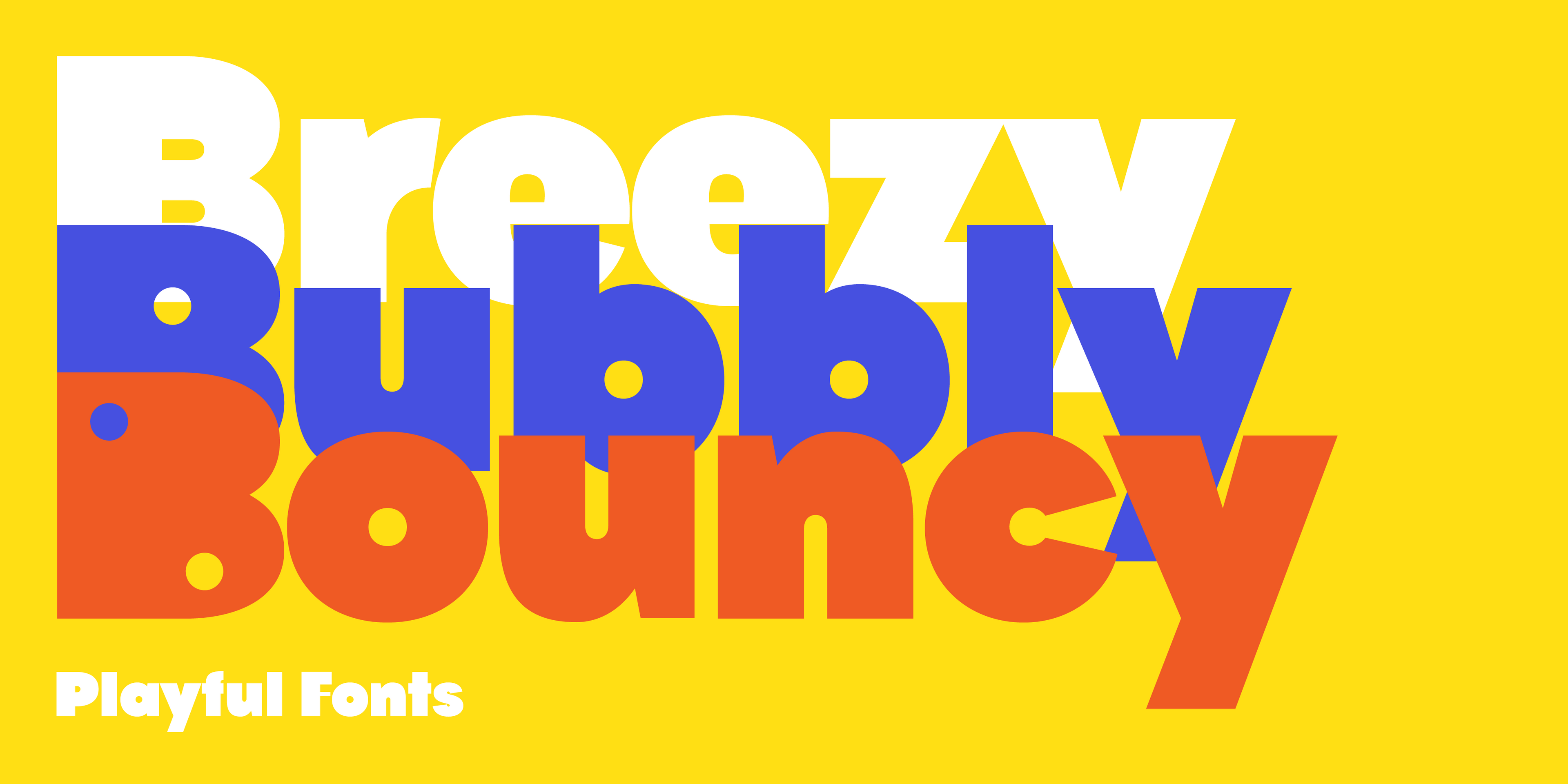
Ya sea que esté trabajando en la marca de un producto para niños o en un libro divertido de leer, las fuentes divertidas son una forma sencilla de comunicar rápidamente el concepto central de su proyecto.
En este artículo, verá algunas de las mejores fuentes gratuitas y comerciales disponibles y explicará por qué son ideales para esta colección de tipografías divertidas y qué tono específico logrará en sus diseños cuando las use.
Fuentes sans-serif divertidas para exhibiciones
Además de encontrar la fuente más divertida y genial para tu proyecto, no olvides probar una variedad de paletas de colores junto con tu texto en nuevas tipografías: los colores realmente pueden marcar una diferencia en cómo respaldan o equilibran el carácter de una tipografía.
Echa un vistazo a Bool arriba. Seleccioné el grosor más audaz de todos, Black. Esta fuente tiene muchos diseños de letras alternativos; en mi ejemplo, estás viendo diferentes letras B. Casi parecen juguetes; cámbialas si necesitas más caracteres de logotipo para tu texto. Más detalles sobre Bool .
Si buscas un estilo más alocado, prueba Pout , una tipografía de contraste inverso. Normalmente conocemos este estilo por las películas del Oeste, pero esta es sans-serif, lo que la hace moderna y divertida. Dado que el peso visual del diseño está en la parte superior e inferior, los trazos verticales de las letras se vuelven finos y las barras horizontales se vuelven llamativas. Los puntos i son redondos y llenos, lo que crea tensión y memorabilidad.
Un poco más estándar a primera vista, esta fuente sans-serif se llama Vole Display , que aquí se muestra en un peso de fuente ligero. Sin embargo, esta tipografía es muy divertida: los tallos inclinados (letras M, W), completamente redondeados y sin tallos que se extiendan por completo hasta la altura de la x para las letras a, m, n y r hacen que esta fuente sea accesible y divertida para los niños. También es un poco suave, creada por los contadores de letras demasiado redondeados, por ejemplo, consulte la letra k.
Tipo de boda lúdica
Por lo general, las fuentes para bodas son elegantes tipo serif o tipografías manuscritas para exhibiciones. Si quieres mantenerte en un ámbito lúdico, es mejor que te quedes con una tipografía manuscrita similar a Lace . Es una tipografía divertida monolineal con muchas opciones de grosor para resaltar o atenuar aspectos de elegancia (más delgada) o infantil (más audaz). Y también viene en una versión redondeada.
Rail es una tipografía divertida y sin duda única que te permite crear elementos de texto elegantes con un toque lúdico. Las letras de esta fuente tienen un tallo fino que conecta los tallos más atrevidos, lo que comunica un concepto de vínculo y conexión. Sus formas redondeadas y geométricas añaden un aspecto moderno al diseño. Echa un vistazo a la familia Rail .
Fuentes serif elegantes para el verano
Ambos tipos de letra pertenecen a la categoría de fuentes serif y ambos tienen nueve grosores, desde superfino a muy grueso. Kijs es informal pero elegante en un grosor más ligero; sus diseños parcialmente cursivos (por ejemplo, las letras i y j) crean un aspecto natural, retro y divertido. Kijs es fácil de instalar para Figma y otras aplicaciones de diseño.
Más sencillas pero muy de moda son las fuentes serif en negrita como Bauhaus Mod . Sus terminales amplias, serifas curvas y formas de letras compactas hacen que esta fuente sea divertida, principalmente cuando se usa en estilos en negrita.
Tipografías de burbujas salvajes para una diversión máxima
Las fuentes de burbujas vienen en todos los estilos y formas. Seleccioné un estilo cursivo más orgánico llamado Skay en la parte superior y la fuente divertida "Loco" en un peso de contraste más ligero debajo. Skay es una tipografía que solo usa mayúsculas y nos recuerda al diseño del logotipo de Skims. Es completa y fluida, lo que hace que el texto de visualización, como logotipos y titulares, sea suave, llamativo y curvo.
Por último, Loco es similar a la fuente del logotipo que se ve en el programa Cocomelon. Algunas letras son más pesadas, por ejemplo, las letras M y N, algunas letras tienen título, por ejemplo, c y l, y todas las letras tienen una tira resaltada incluida, lo que crea un efecto 3D para los mejores diseños veraniegos divertidos.
Fuentes de Google gratuitas
Si buscas una integración web sencilla de tus fuentes u opciones gratuitas para Canva, te recomiendo que también mires las siguientes tipografías divertidas de Google:
– Borel es una tipografía manuscrita que presenta un aspecto escolar.
– Caprasimo es una fuente serif redondeada y atrevida que nos recuerda a los años 70.
– Titan One es una fuente de burbuja divertida y moderna.
Todas las fuentes de Google enumeradas anteriormente solo tienen un estilo de fuente gratuito: es mejor usarlas para mostrar texto, como titulares.